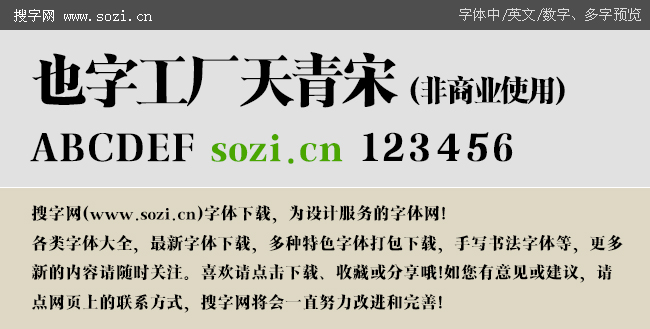
也字工厂天青宋
搜字网给大家提供一款也字工厂天青宋(非商业使用)中文字体下载,也字工厂天青宋中宫偏宽,字形方正,饱满充盈。 笔画粗细对比强烈,横细竖粗,刚柔并济;起笔行笔又借鉴了楷书造型,笔画尽可能最大限度舒展,造型柔美典雅。 搭接处保留了起笔、收笔的造型,增强了字体的书写感,局部的特殊设计带给整体更具人文气息的视觉观感,而不至于僵硬呆板。适合应用于标题设计、海报设计、网页设计等应用(此字体为个人非商用版,商用可以联系:官方网址:https://yefont.com/home,联系方式:13798980448)。